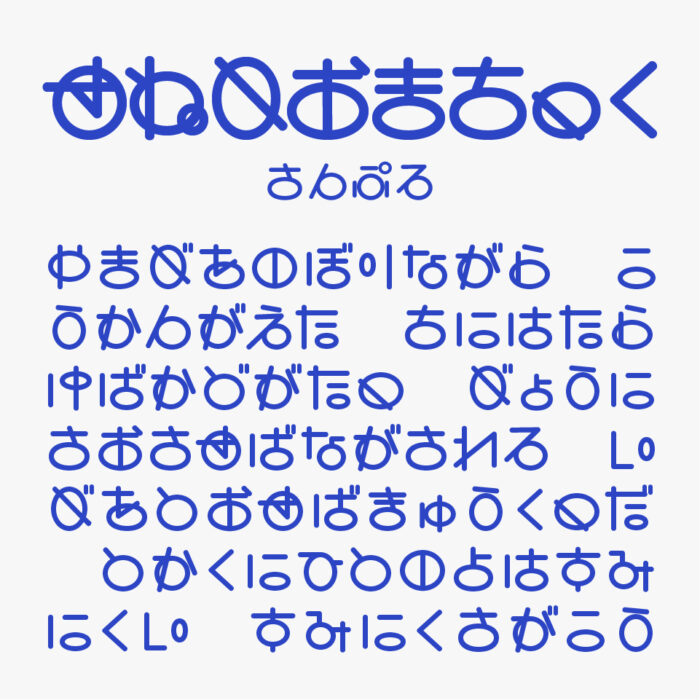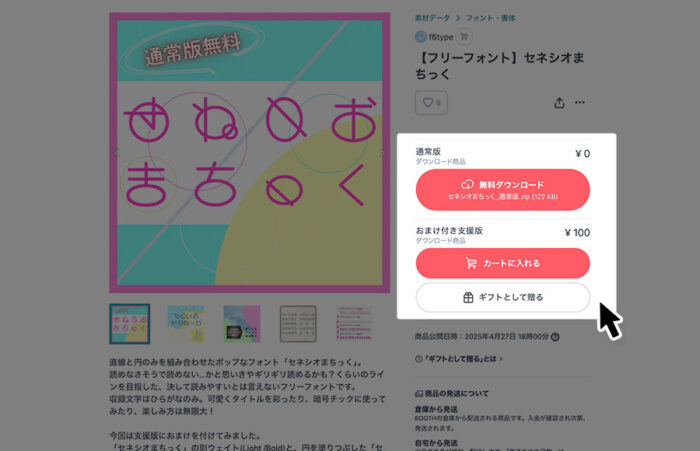
セネシオまちっく
セネシオまちっくフォントは、直線と円を組み合わせて作られたデザインフォントです。
すべてのひらがな文字の一つひとつが直線と円だけで作られているので、暗号のような文字にも見えますが、じっくり見ていると読めてくるユニークなデザインです。見る人の心をくすぐる遊び心たっぷりのスタイルに仕上がっています。
セネシオまちっく